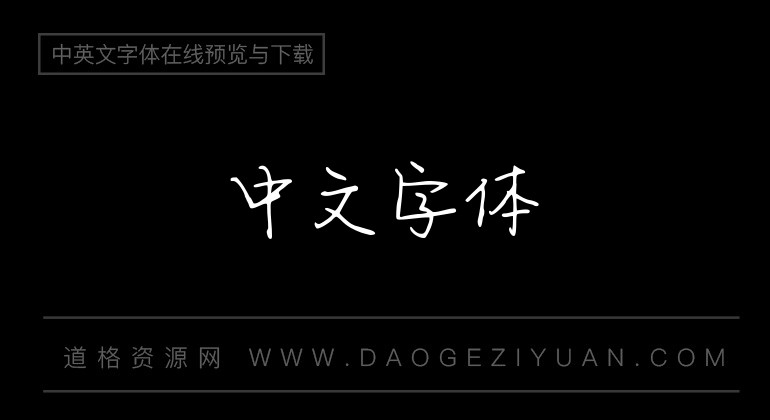
Aa小轶行楷是一款简约古典的汉字字体,由一位经验丰富的设计师精心设计,具有清新潇洒的风格。字体采用细腻的线条,笔画流畅,把汉字的精美与古典的美感完美结合,表现出一种清新淡雅的气质。字体细节处理精致,结构清晰,非常适合用于书法、篆刻、排版、绘画等领域。文件名:AaXiaoXingKai-2.ttf
Aa小轶行楷是一款非常不错的手写艺术字体,具有很好的视觉感,适合于文化类的宣传设计、商业类品牌的广告和产品包装设计以及个性化文字排版等较多场景。